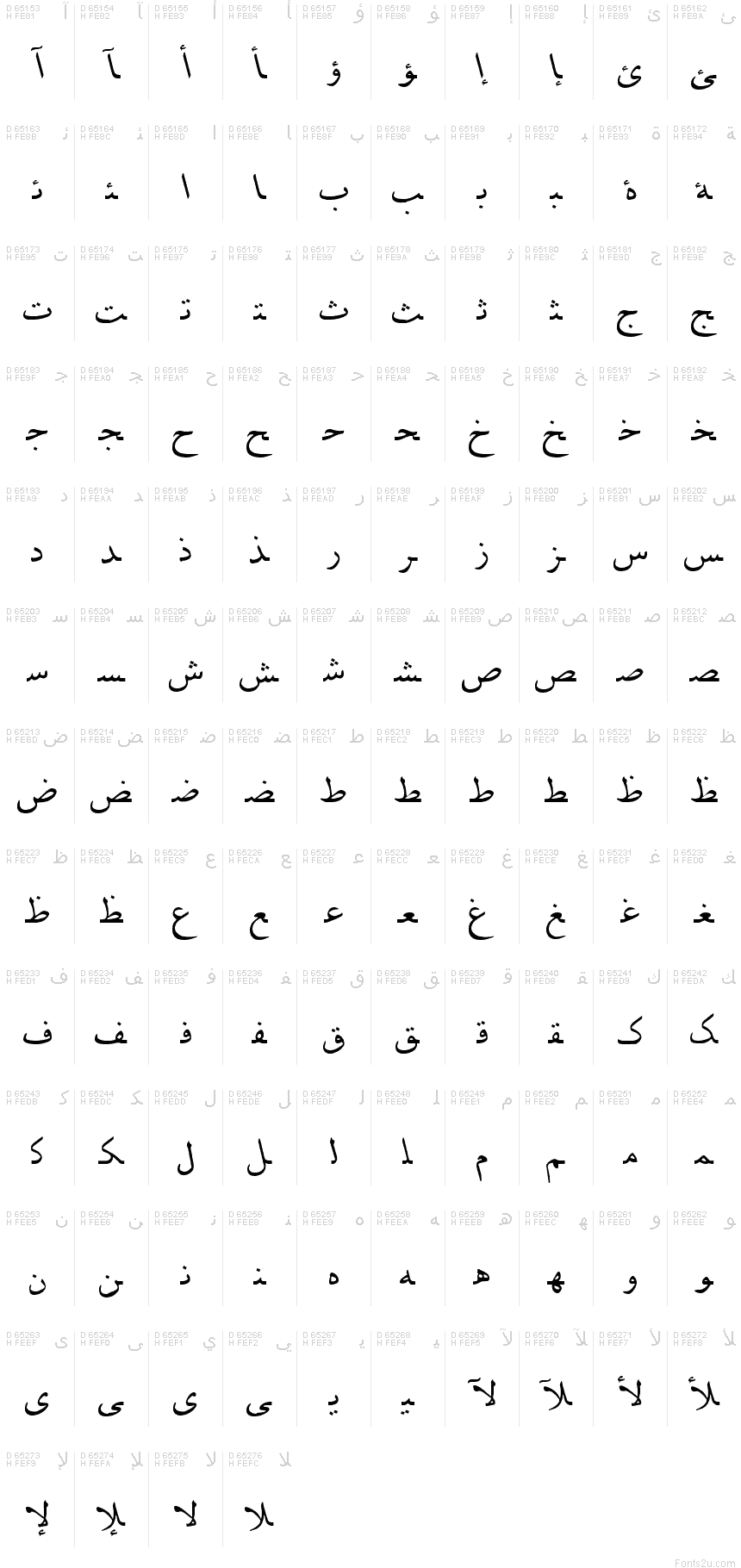
B Mashhad Italic von Borna Rayaneh ist eine kostenlose arabische Kursivschrift mit fließendem, handschriftlichem Rhythmus. Die Buchstaben neigen sich dynamisch nach vorne und verbinden sich in schwungvollen Zügen. Eine Mischung aus kompakten, kräftigen Formen und schnellen Aufstrichen verleiht diesem Font eine ausgeprägt kalligrafische und moderne Ästhetik.
Die Schrift entfaltet ihre Wirkung ideal auf kulturellen Plakaten, Buchtiteln, in Magazin-Überschriften, auf Einladungskarten und in Logos, die eine persönliche arabische Note benötigen. Als kostenloser Font eignet sie sich hervorragend für kurze Anzeigentexte, Titelzeilen und markante Schriftzüge, da die geneigte Bewegung und die enge Linienführung selbst kurzen Phrasen Dynamik und eine zeremonielle Eleganz verleihen.